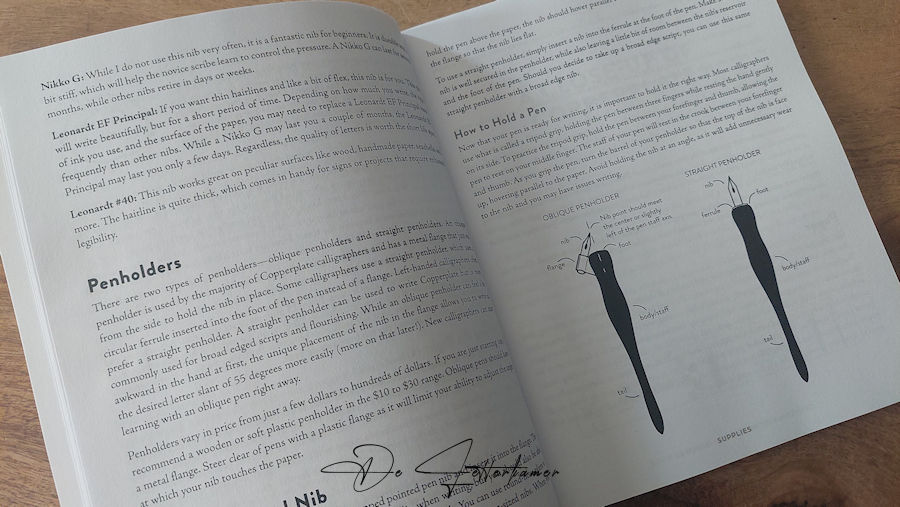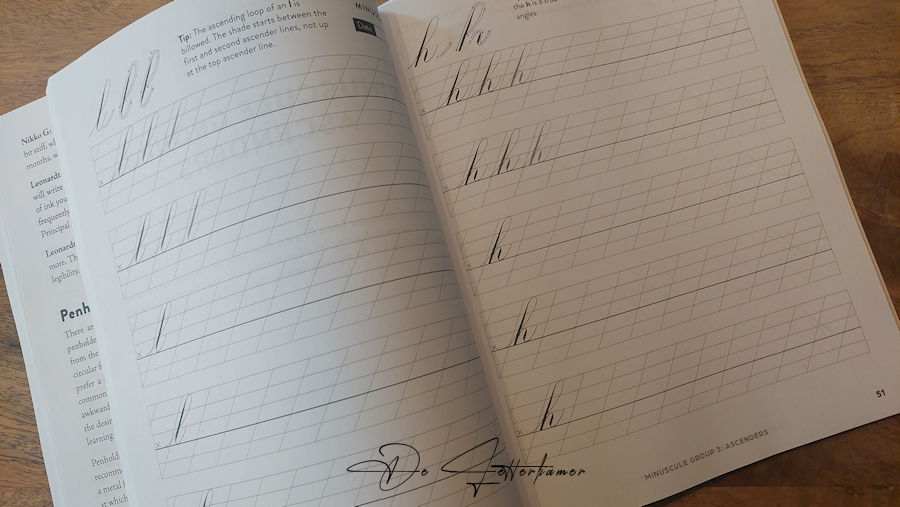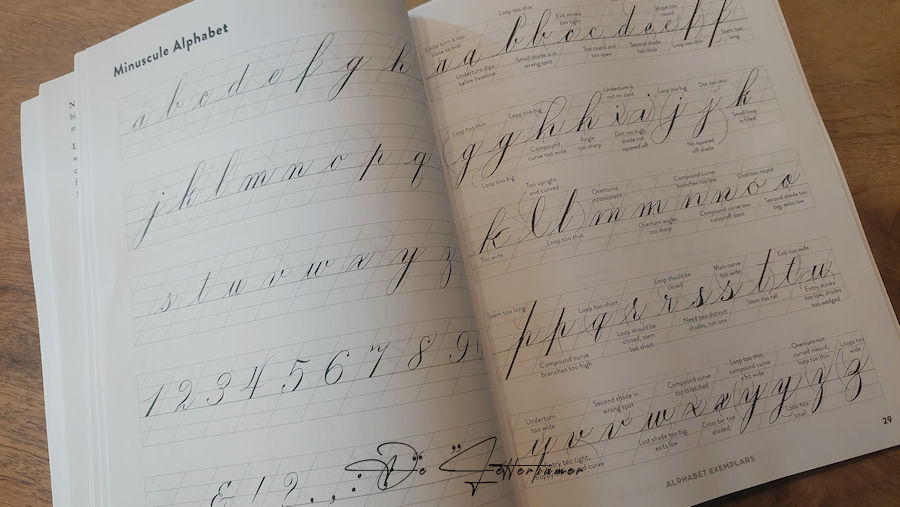
Mijn boek, mijn oefenboek is geleverd, er is een korte inleiding in verband met de basisvormen, een voorbeeld van de kleine letters en hoofdletters, en wat er allemaal fout kan lopen.
Bij elke letter is er een voorbeeld hoe je een letter moet schrijven. Het zijn verschillende basisvormen die 1 letter vormen.
De basisvormen moet je eigenlijk eerst heel goed kunnen schrijven en zonder na denken.
Deze letters worden, als men alles onder de knie heeft, aan elkaar geschreven. Dat is uiteraard de bedoeling.
We gaan aan de slag, maar eerst nog de basisvormen. Een uurtje is voldoende, dit staat er ook in, in dit boek, enkele keren per week.